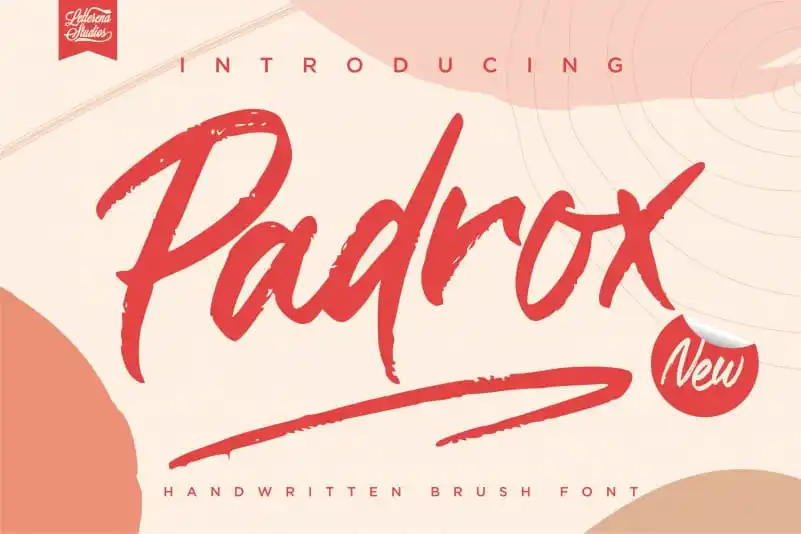
A fonte Padrox Brush é uma delícia para quem procura um estilo que transborda personalidade e expressão artística. Desenvolvida pelo designer letterenastudios, ela se destaca como uma opção perfeita para aqueles que buscam um estilo brush pen que reflete criatividade e originalidade em seus projetos de design gráfico. Com linhas suaves e detalhes intrigantes, Padrox Brush traz vida e movimento a qualquer projeto onde for utilizada. Suas curvas fluidas e traços elegantes permitem que você crie texturas vibrantes e textos dinâmicos que se destacam em qualquer ambiente design. Seja para adicionar um toque único a sua logo, criar uma capa de ebook memorável ou decorar um site com uma estética inovadora, Padrox Brush está à altura do desafio. Personalizar é o nome da jogada com essa fonte: pode-se ajustá-la ao seu gosto e às necessidades específicas do projeto sem perder sua essência. Ideal tanto para uso pessoal quanto para projetos que não requerem fins comerciais, Padrox Brush é uma escolha segura se você está buscando a perfeita fusão de qualidade gráfica com estilo único.